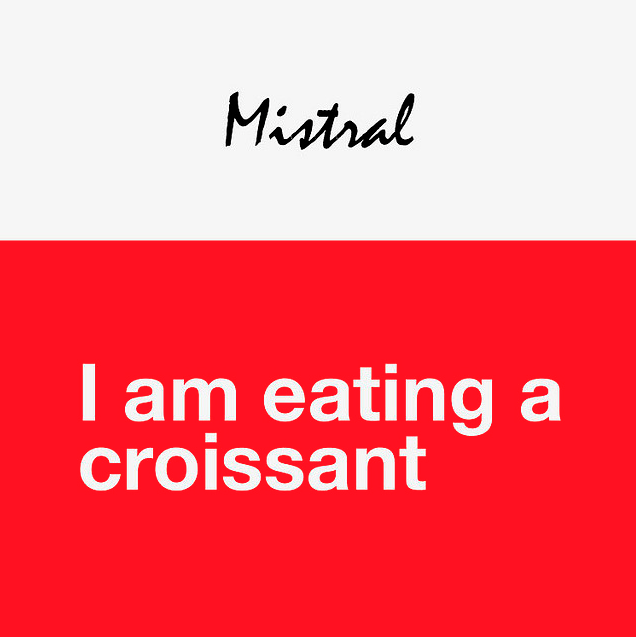
Son muy pocos los que siguen escribiendo a mano, pero eso no significa que el psicoanálisis a través de la tipografía no se pueda usar. Entre la variedad de fuentes y familias tipográficas, elegir entre una y otra habla de tus criterios estéticos y también psicológicos.
El diseñador Lars Willem Veldkamp ha creado en el proyecto ‘Typocalipse’ un repaso con los mensajes subliminales que nos envían 40 fuentes tipográficas.
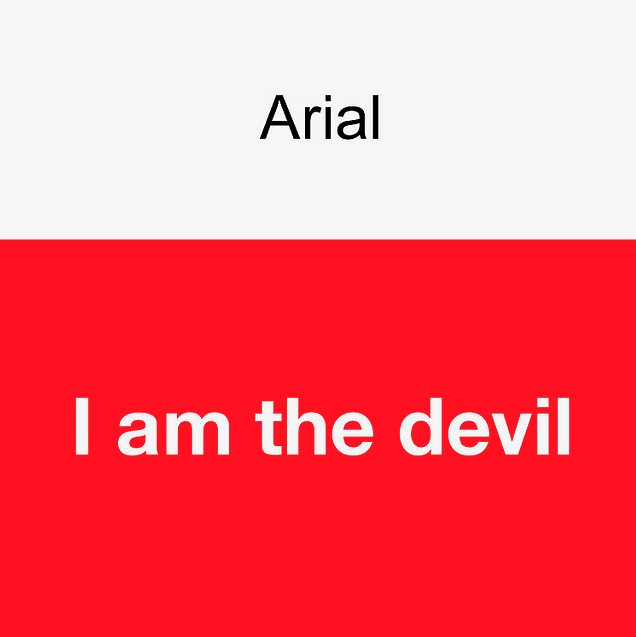
Seguro que muchos diseñadores creen que estas dos descripciones deberían invertirse: Comic Sans debería ser el demonio y Arial la mano de Dios. ¡Pues se admiten propuestas! No tiene por qué ser Lars el único diseñador en hacer interpretaciones tipográficas.
Otros análisis de Lars Willem Veldkamp son más nacionalistas. Mistral es la fuente de un croissant francés (también encaja con una baguette o cualquier producto de Boulangerie). Y Didot también tiene un aire al país galo pero... más bien recuerda a una “bailarina” del Moulin Rouge. En ésta sí que estamos bastante de acuerdo... ¿o no?
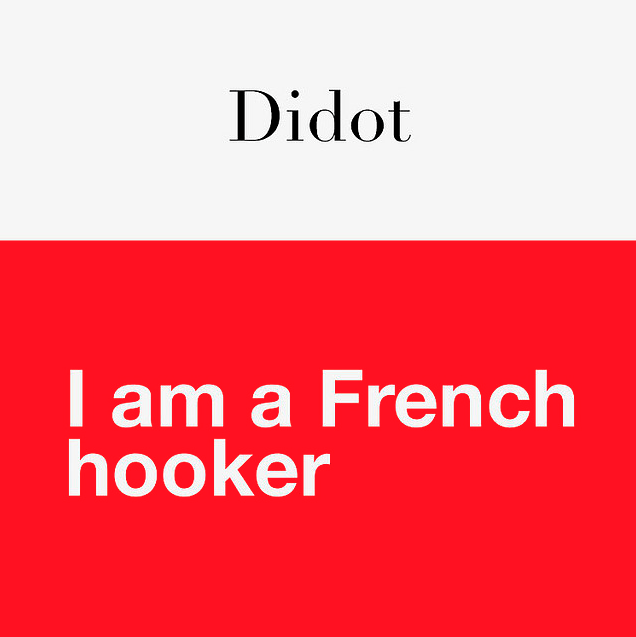
También coincidimos en que cuando usamos una tipografía inspirada en la máquina de escribir, de repente nos sentimos como auténticos poetas. Courier New te hará sentir como Kevin Spacey. Probablemente escribirás un guión de Hollywood. Y American Typewritter es una fuente nostálgica. Seguramente la usó Tenesse Williams para escribir ‘Un Tranvía llamado Deseo’...
De entre las cuarenta fuentes que ha analizado Lars Willem Veldkamp, os dejamos con una selección de las mejores. Si os engancháis, podéis verlas todas en su cuenta de Flickr.